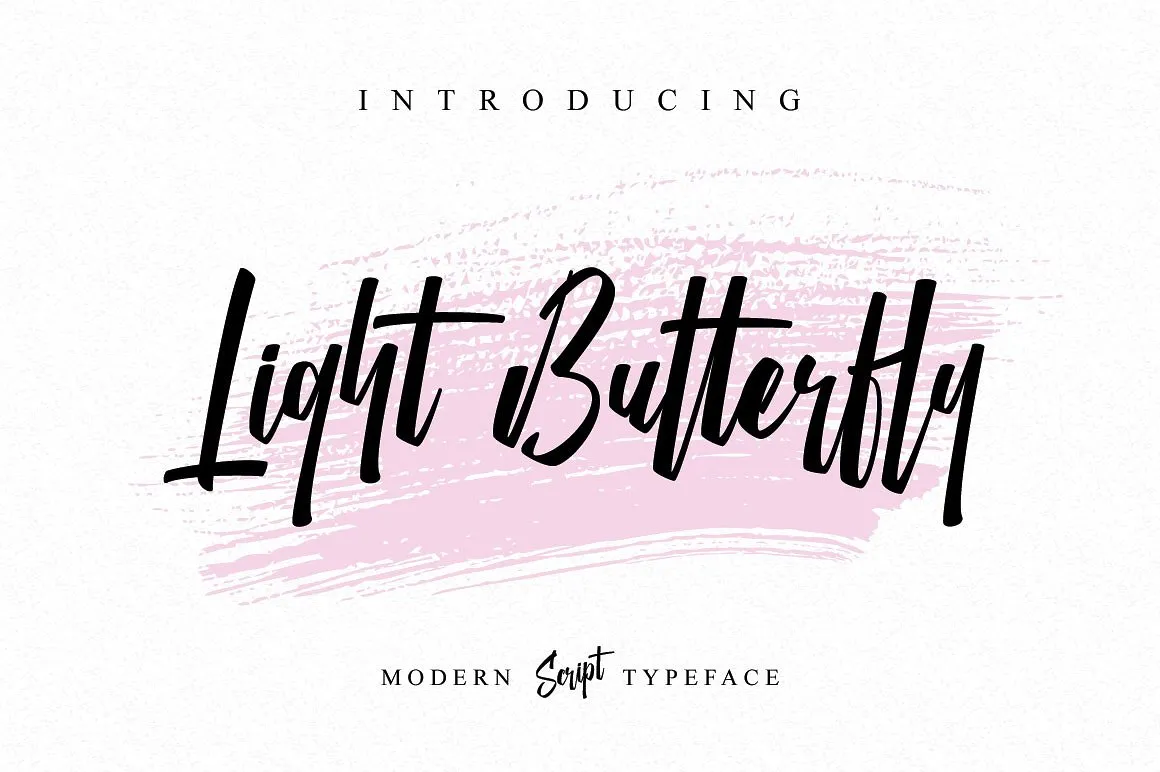
Introduzimos a Light Butterfly Script Font! Esta é uma tipografia de letra cursiva moderna. Foi criada por individuel e agora está disponível gratuitamente para download na Creativemarket. A Light Butterfly traz um estilo natural aos seus projetos, além da fonte padrão. Essa premium font inclui ligaturas (caracteres personalizados), o que a torna perfeita para uso em diversos fins, como convites de casamento, logotipos, selos, desenho de camisetas, cartas, maquetagens com citações, embalagens de produtos, cabeçalhos, blogs, grafitti e headlines em sites. Experimente esta exclusiva coleção e descubra sua incrível potencial para design.